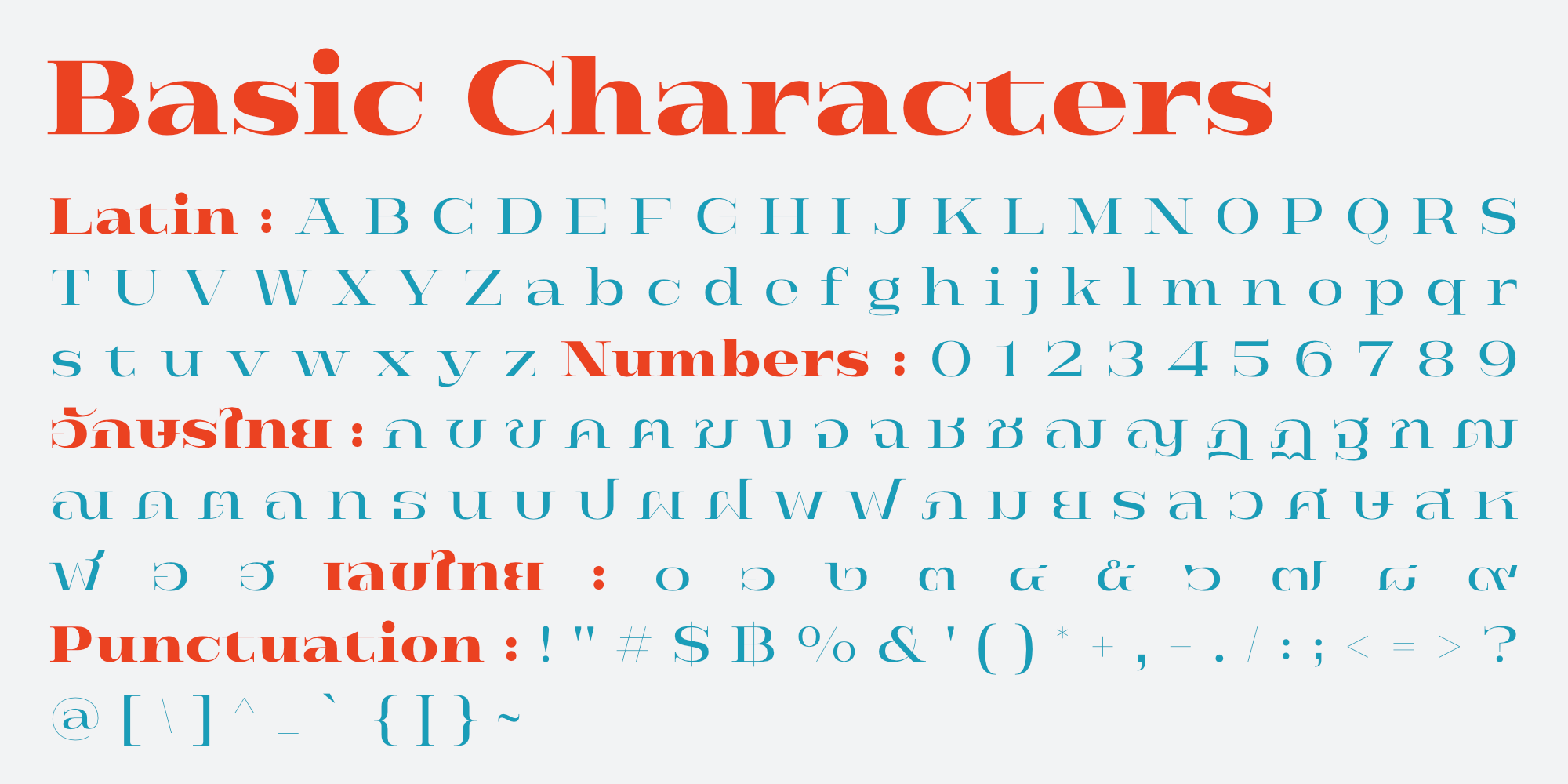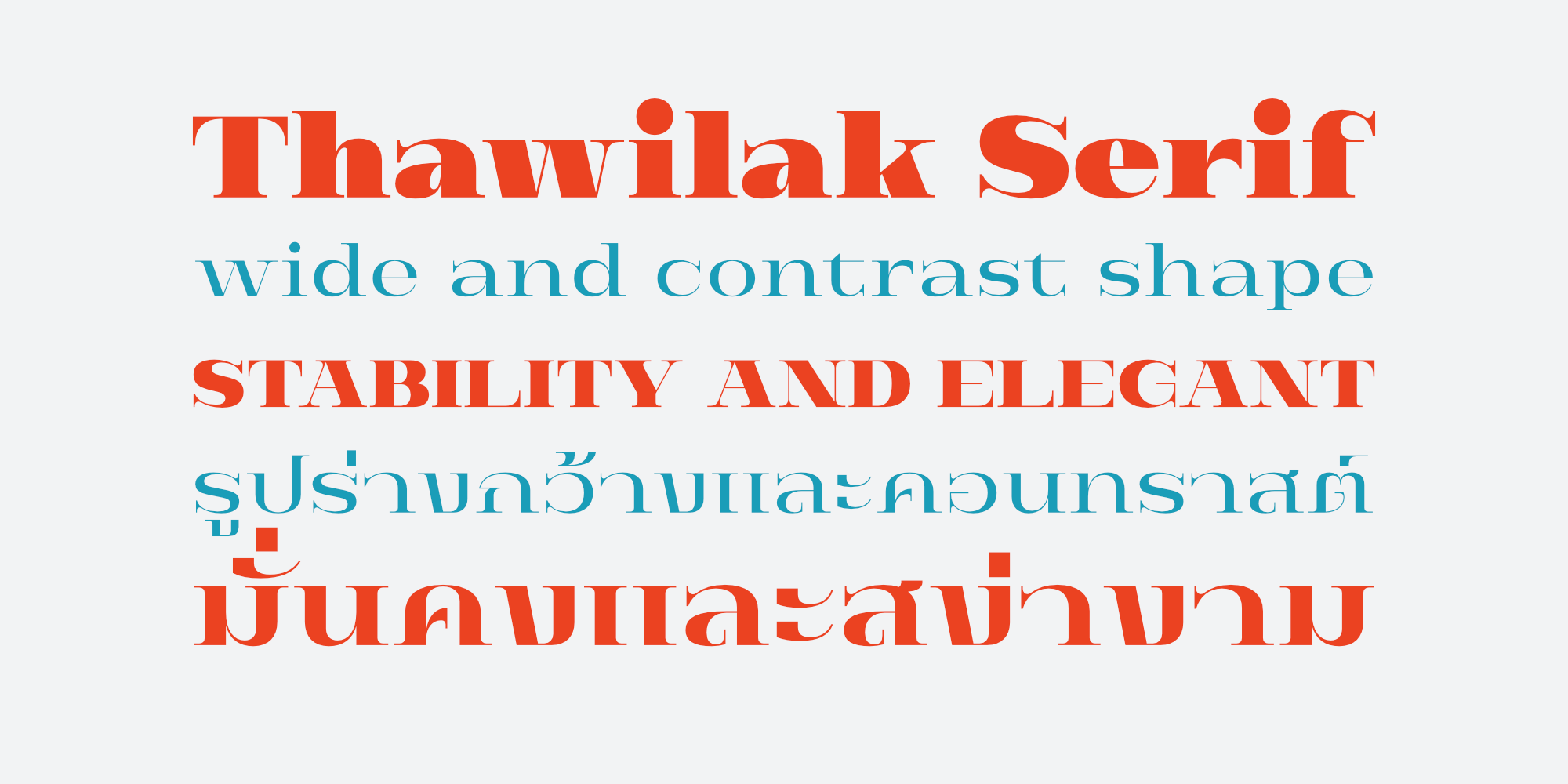
ทวิลักษณ์ เซอริฟ | Thawilak Serif
ชื่อฟอนต์ : ทวิลักษณ์ เซอริฟ | Thawilak Serif
ขอแนะนำ Thawilak Serif แบบอักษรที่สวยงามและละเอียดอ่อนที่รวบรวมแก่นแท้ของความสง่างาม และความมั่นคง ด้วยคอนทราสต์สูงและรูปทรงที่กว้าง ฟอนต์นี้มีเสน่ห์เหนือกาลเวลาซึ่งจะสร้างความประทับใจให้กับผู้พบเห็นได้ไม่รู้ลืม Thawilak Serif คือตัวแทนแห่งความงามและความมั่นคง ไม่ว่าจะใช้ในสื่อสิ่งพิมพ์หรือสื่อดิจิทัล จะเพิ่มสัมผัสของความมีระดับและความน่าเชื่อถือให้กับโปรเจ็คต่างๆ ไม่ว่าจะเป็นบทความ การสร้างแบรนด์ หรือบรรจุภัณฑ์ที่หรูหรา
Introducing "Thawilack Serif," a stunning and sophisticated typeface that captures the essence of elegance, and stability. With its high contrast and wide shape, this font exudes a timeless charm that is sure to make a lasting impression. Thawilack Serif is the embodiment of beauty and stability. Whether used in print or digital media, it adds a touch of class and credibility to any project, be it article layouts, branding materials, or luxury packaging.
Creator : อานุภาพ ใจชำนาญ (Anupap Jaichumnan)